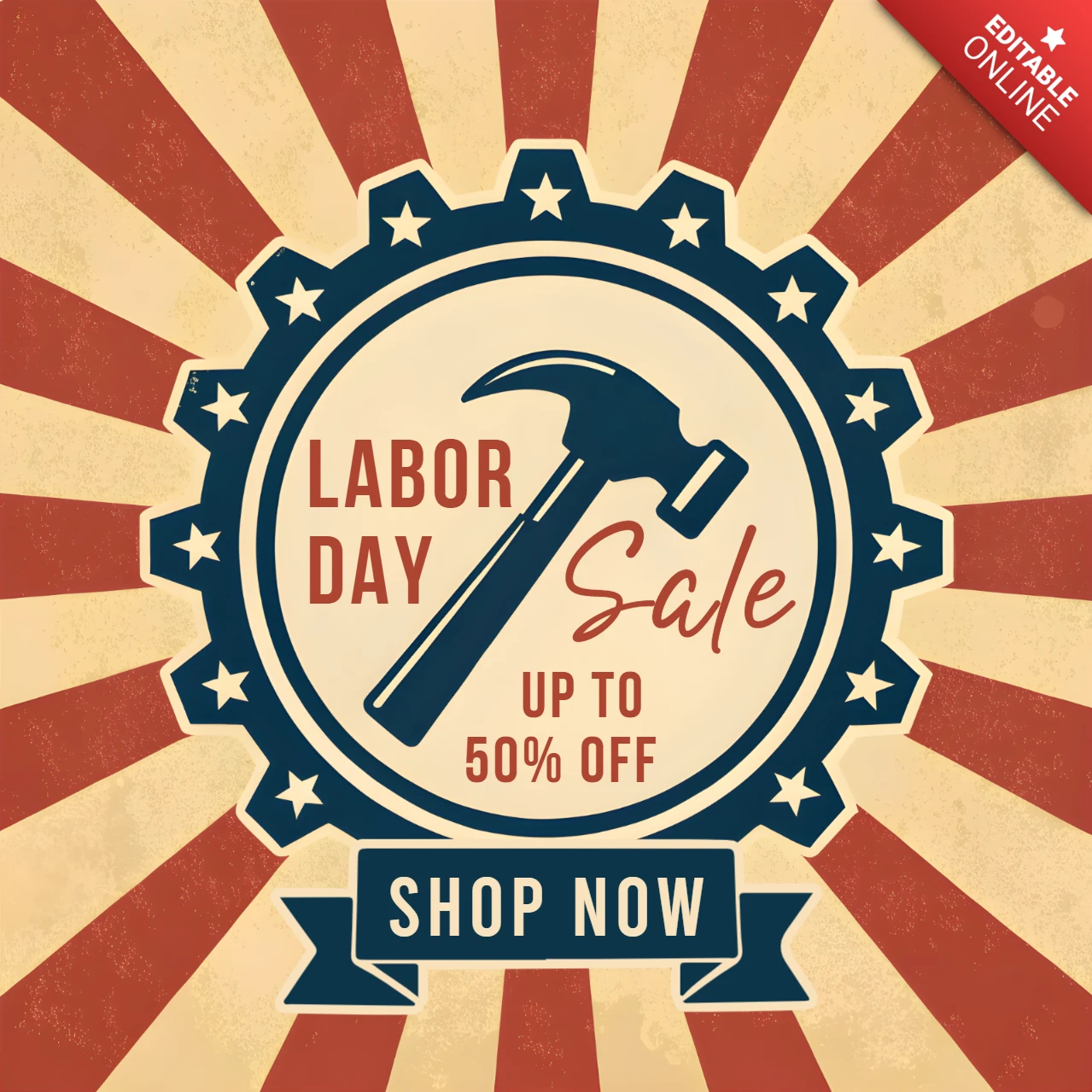
Modèle rétro de vente pour la fête du travail avec l'icône du marteau et une typographie audacieuse
Éditer dans Design Studio Télécharger en JPGCréez un message festif pour la fête du travail avec notre modèle coloré "americana", doté d'une typographie audacieuse et d'un design de badge rétro - parfait pour promouvoir votre vente sur les médias sociaux !